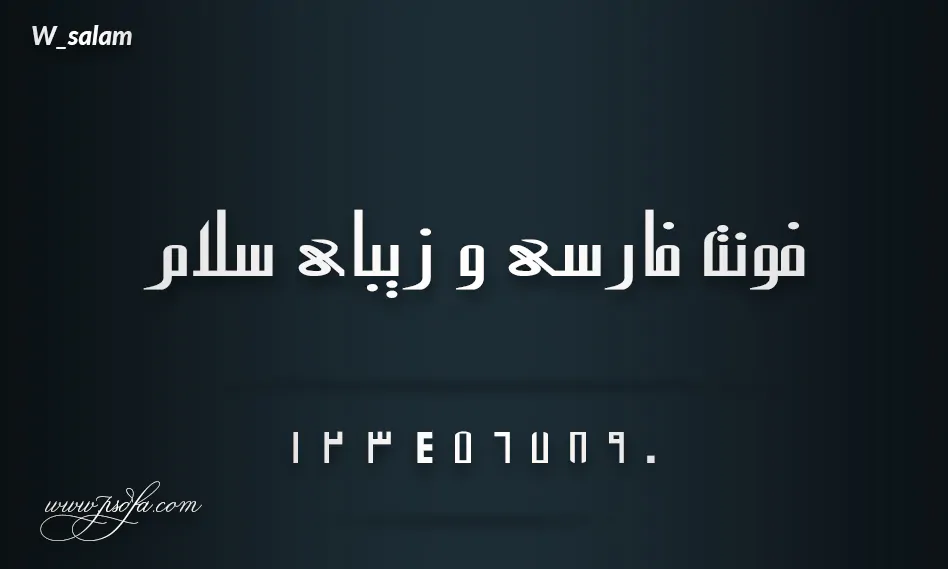
فونت سلام W_salam Farsi Font
فونت فارسی سلام
در این قسمت از سایت شاهد فونت فارسی سلام W_salam Farsi Font مناسب جهت استفاده در طراحی و گرافیک می باشید. فونت سلام در قالب یک فایل ttf در سایت بارگذاری شده است که با نصب این فایل در پوشه فونت های سیستم قادر به استفاده از آن در تمام نرم افزارهای گرافیکی و ویرایشگر متن از جمله نرم افزار فتوشاپ ، مجموعه نرم افزار آفیس و … خواهید بود. فونت فارسی سلام در وزن ضخیم معمولی (Regular) طراحی شده است که از آن می توان در طراحی انوع تراکت ، پوستر ، کارت ویزیت ، بروشور و … استفاده نمود.